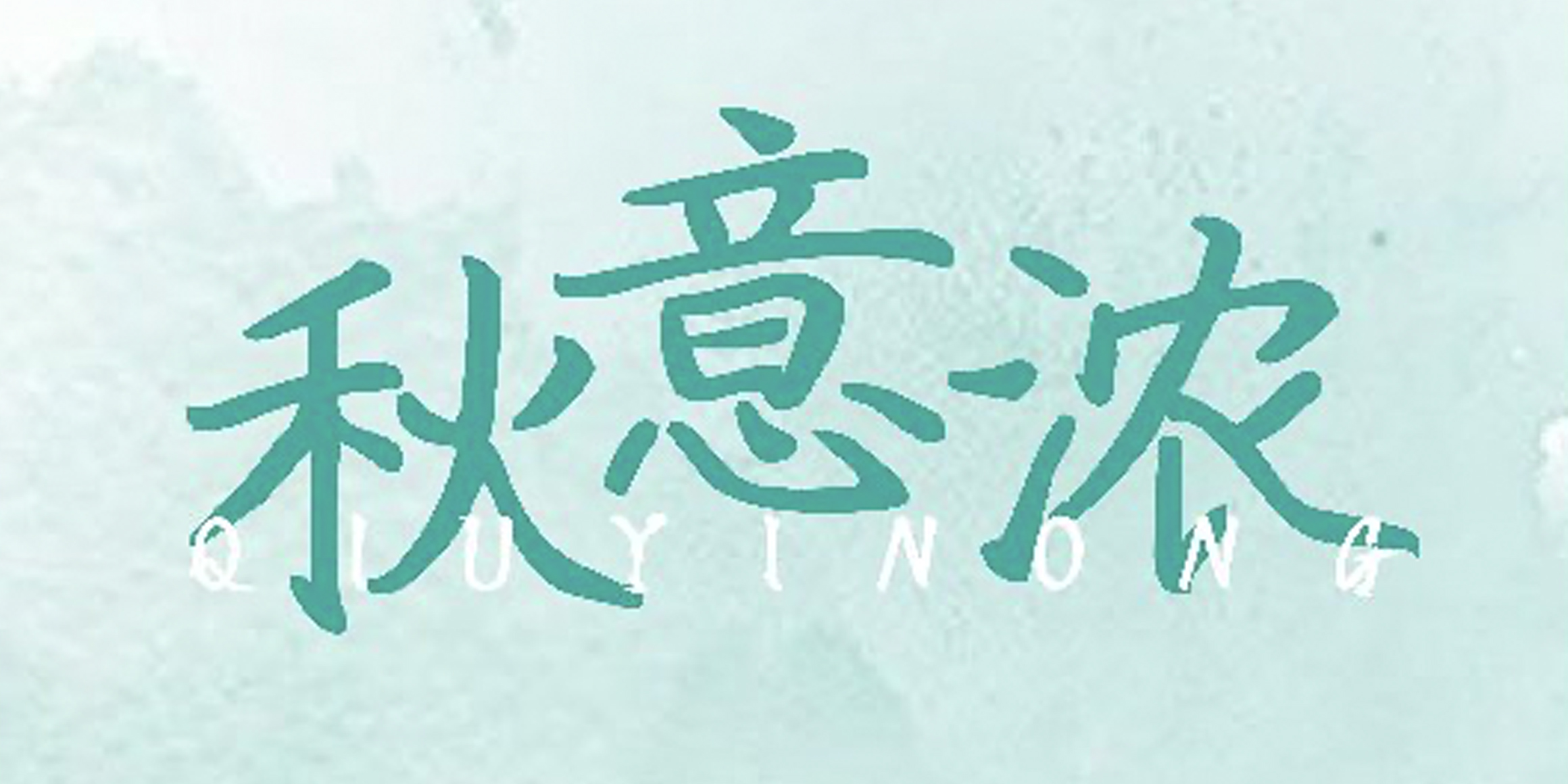
AR MaoKaiGB
07 Bold
09 Heavy
AR MaoKai 시리즈는 심플하면서도 힘있는 인상을 갖고 있다. 펜글씨 형태의 라인과 좁은 폭의 디자인이 아름다운 캘리그래피를 연상시키기도 한다. 주로 소설이나 에세이의 제목이나 소제목에 적합하다.
폰트명 뒤에 붙은 GB라는 표기는 간체의 문자코드를 뜻한다. 간체란 중국에서 주로 사용하며 필획을 줄이고 자형을 간단하게 만든 한자다. 대만, 홍콩, 마카오 등에서 사용하는 번체(B5)와는 달라 잘못 적용할 경우 글립이 제대로 표기되지 않거나 다른 글립으로 표기되는 문제가 발생할 수 있다.